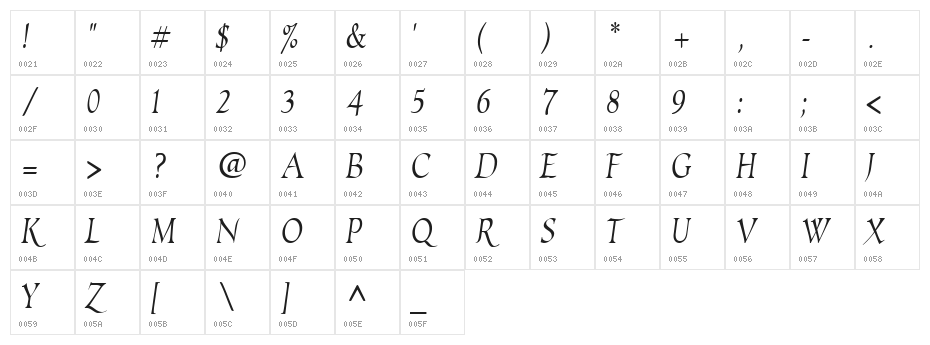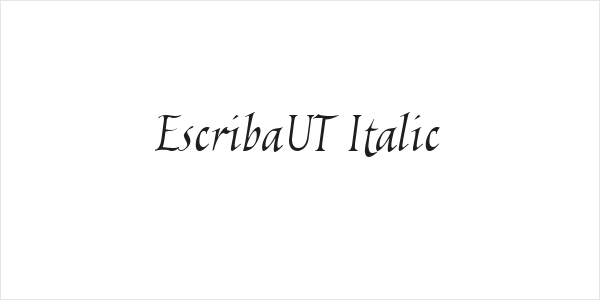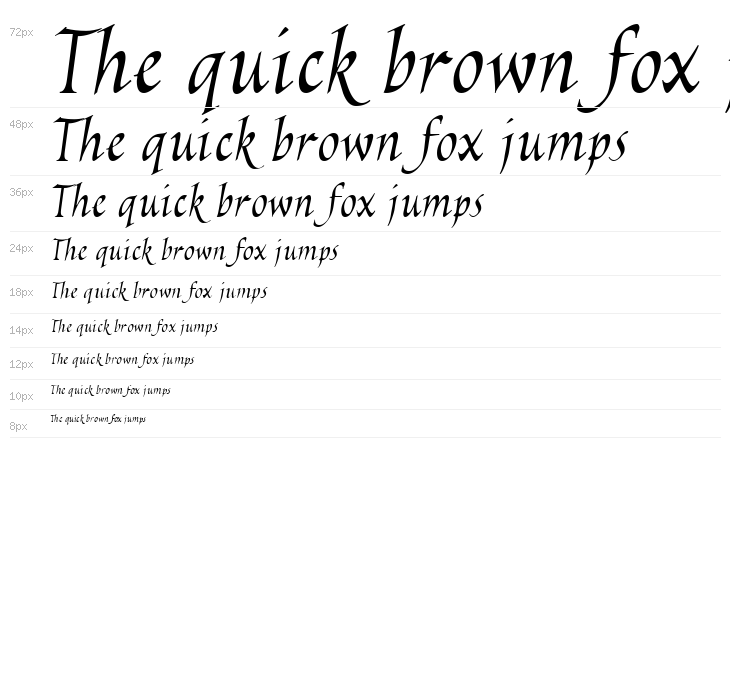
EscribaUT Italic Font
| श्रेणियाँ | Script |
| इटैलिक | Yes |
| समग्र शैली | Classic |
| उपयोग का मामला | Headlines, Logos, Invitations |
| सुझाए गए प्रोजेक्ट | Suitable for wedding invitations, formal event programs, elegant branding, and sophisticated editorial design. |